Cartograph CF
Connary Fagen が作っている、ぱっと見普通の Sans Serif っぽいが、小文字の a/r のハネやトメの部分が隅溜まりのようになっていてかわいい…
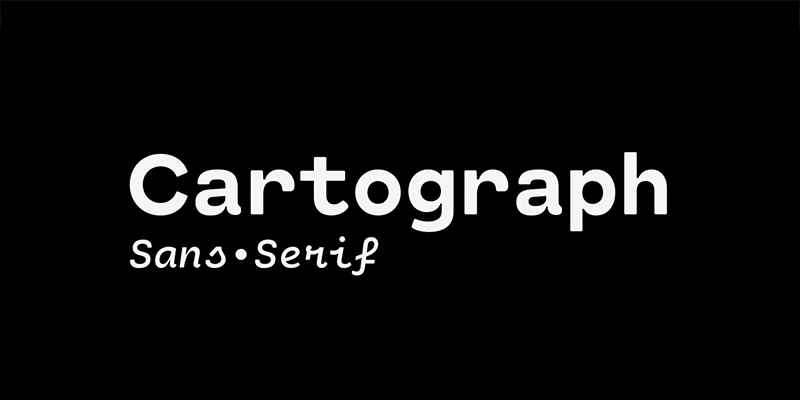
Articulat CF
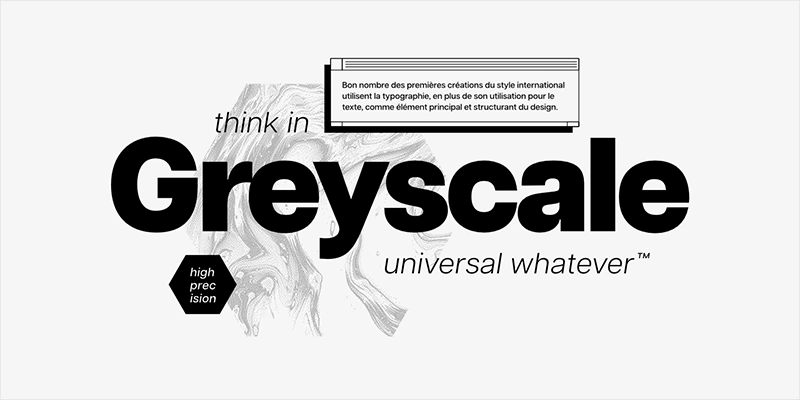
こちらも Connary Fagen が作っているフォント。GROTESQUE 系フォントだが、『G』の形がかわいい
Greycliff CF
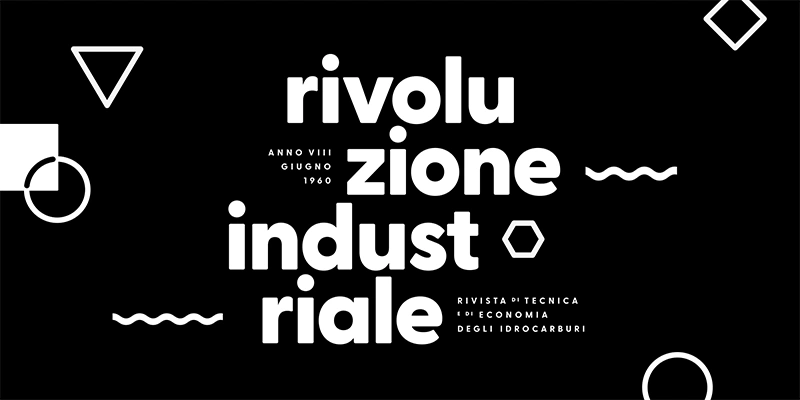
こちらも Connary Fagen 作。こちらは使いやすい Geometric なフォント
Mina
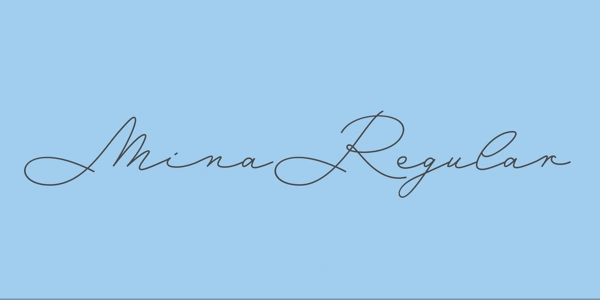
ワンポイントで使うとよさそうなフォント。視認性は0なので、メーンな部分でつかうのはやめた方がよさそう
Auto
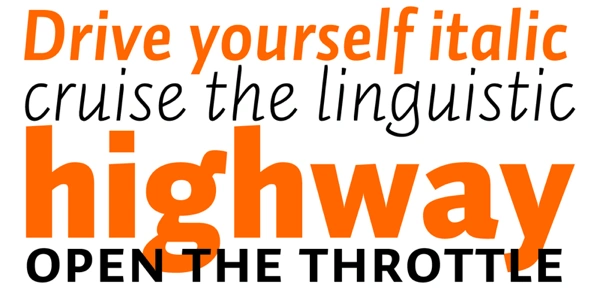
italic が結構面白いフォントです。ピシッと決まって無くて少しカーブがあるので優しい印象になります
Minerva Modern
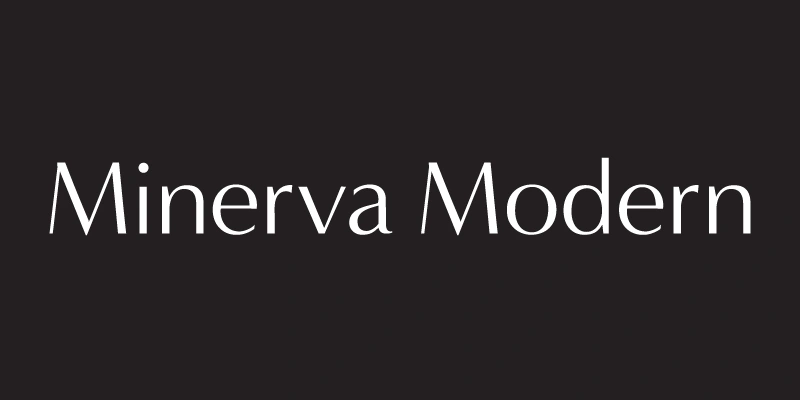
Serif 体のような雰囲気は作りたいけど、そこまでかしこまりたくないときに役に立ちそう
Aisha
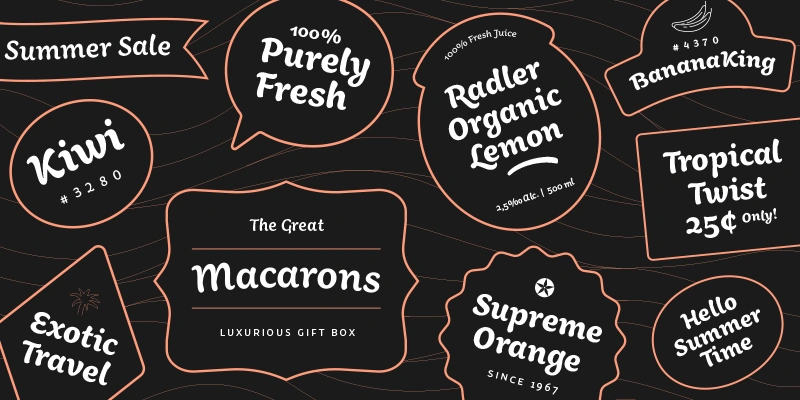
筆記体までは行かないけど、筆跡があるようなフォント。いいアクセントです…。
Capitol
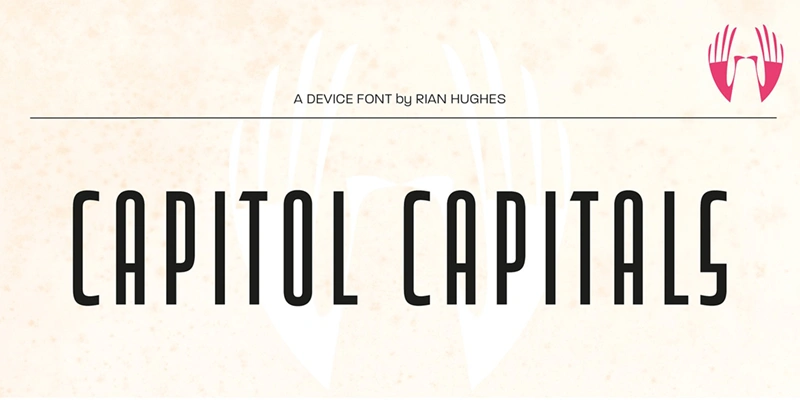
ワンポイントで使うとかわいい。筆記体よりは視認性が高いので活躍しそう
JAF Domus Titling
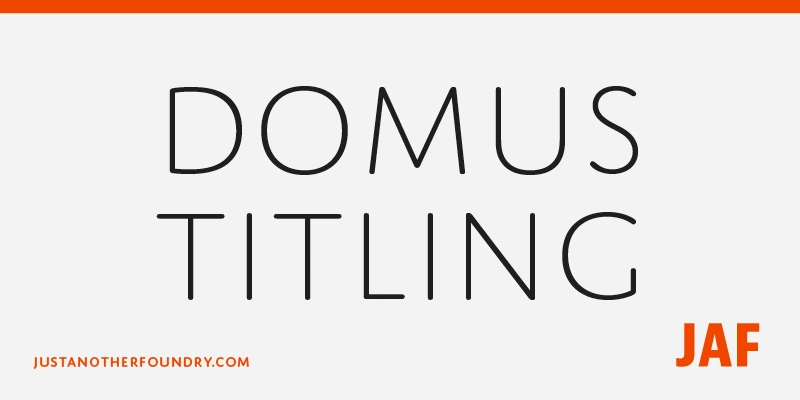
大文字フォント。細字もかわいいけど、太字もかなりかわいい。『Q』がかわいい…
Filson
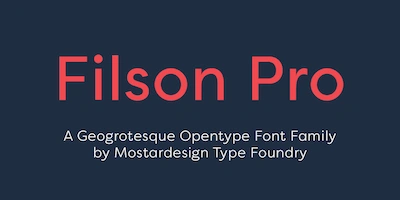
Geometric なフォントだけど、小文字『k』や『p』が癖があり、目を惹くフォント
Obliqua Sans
Verdana のようなちょっとかわいいが残っているフォント